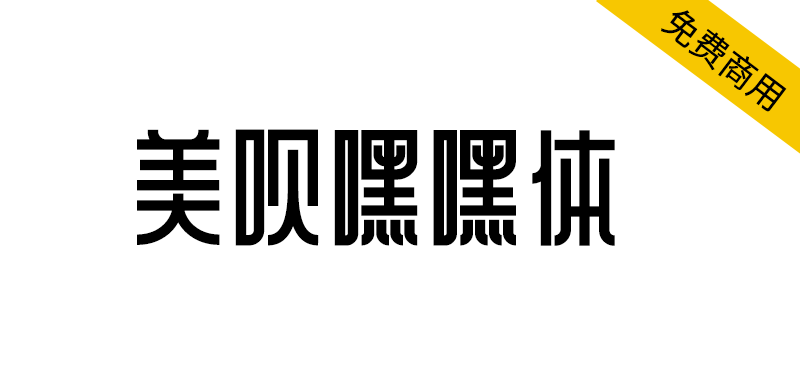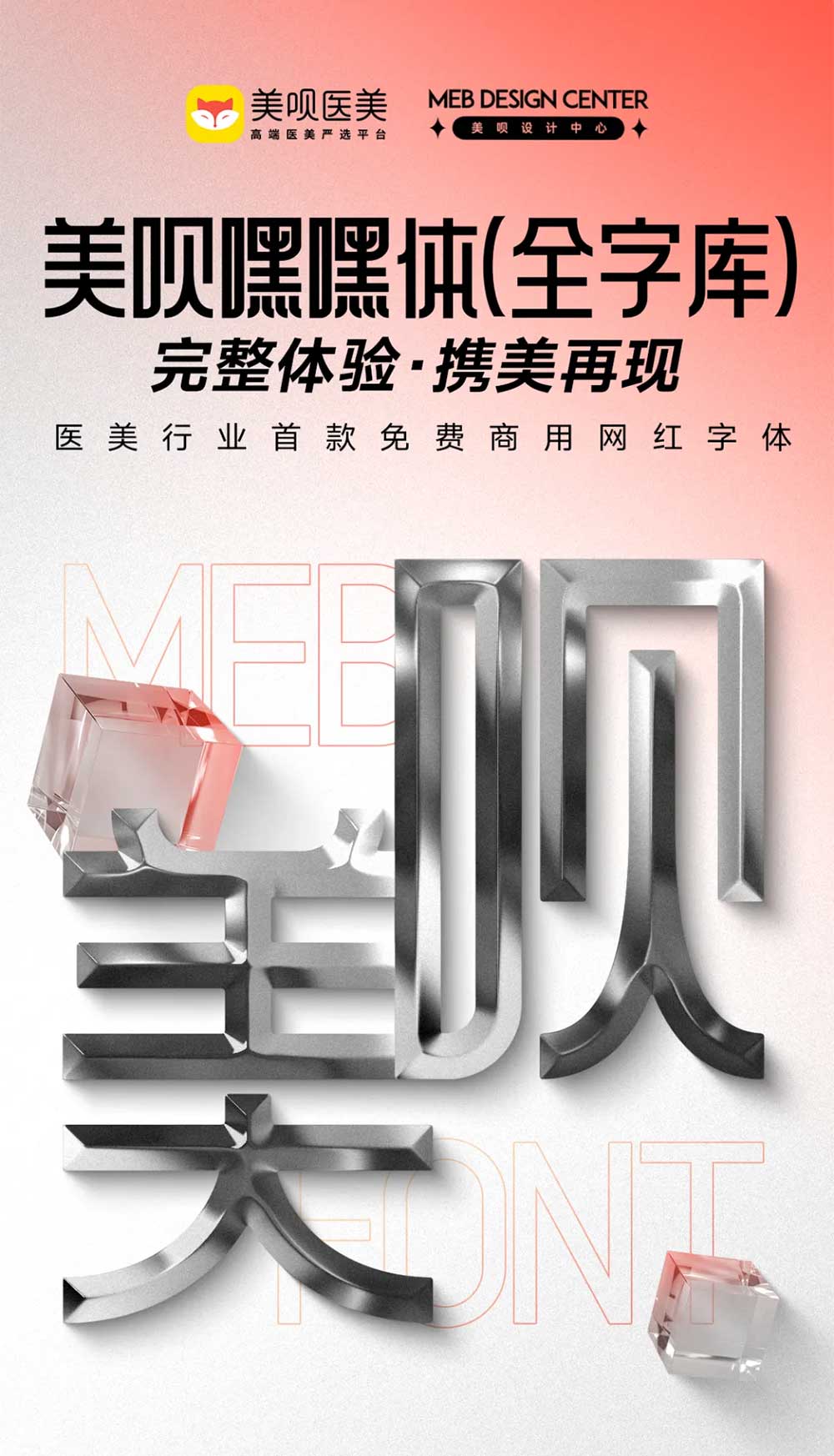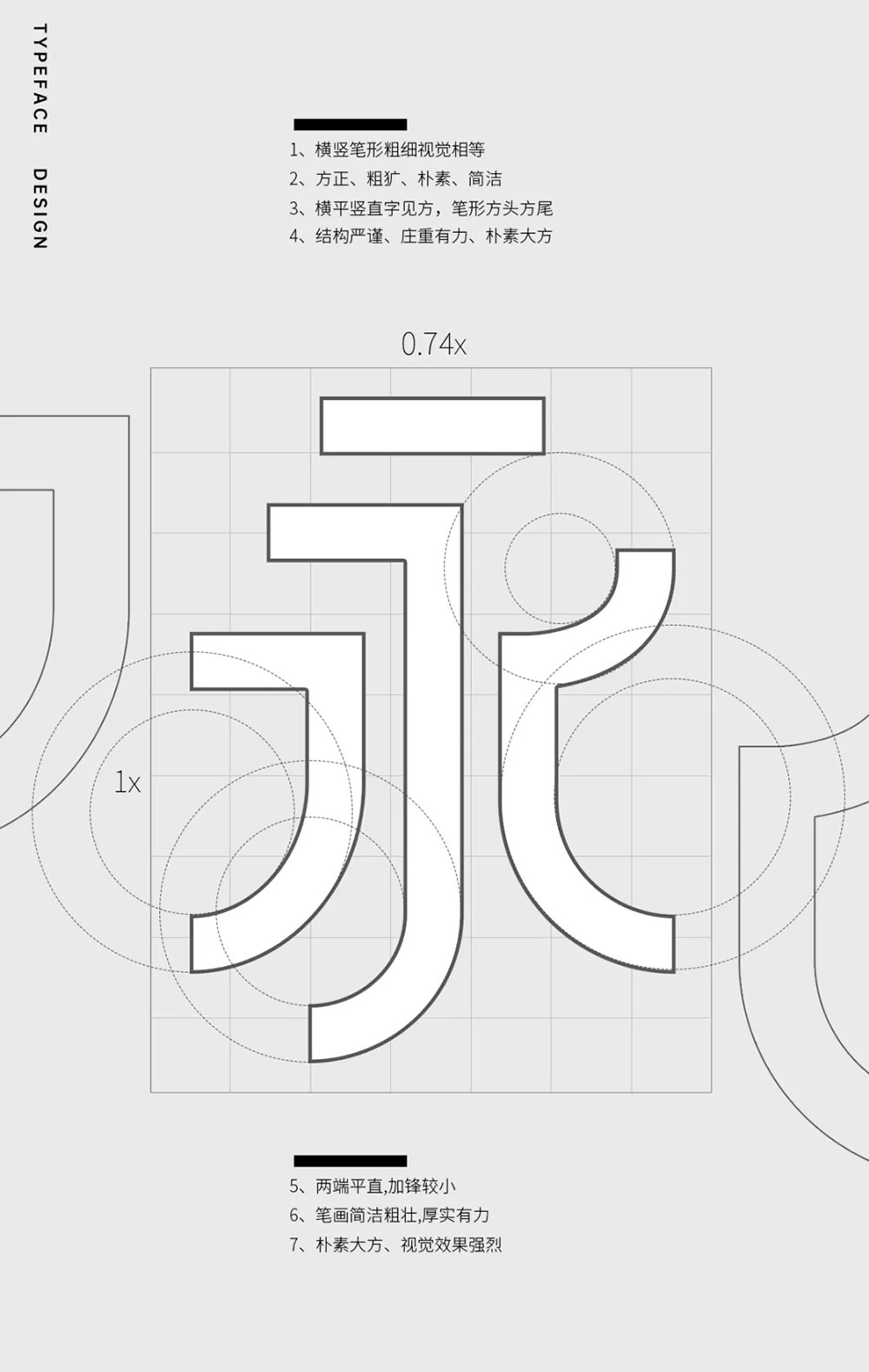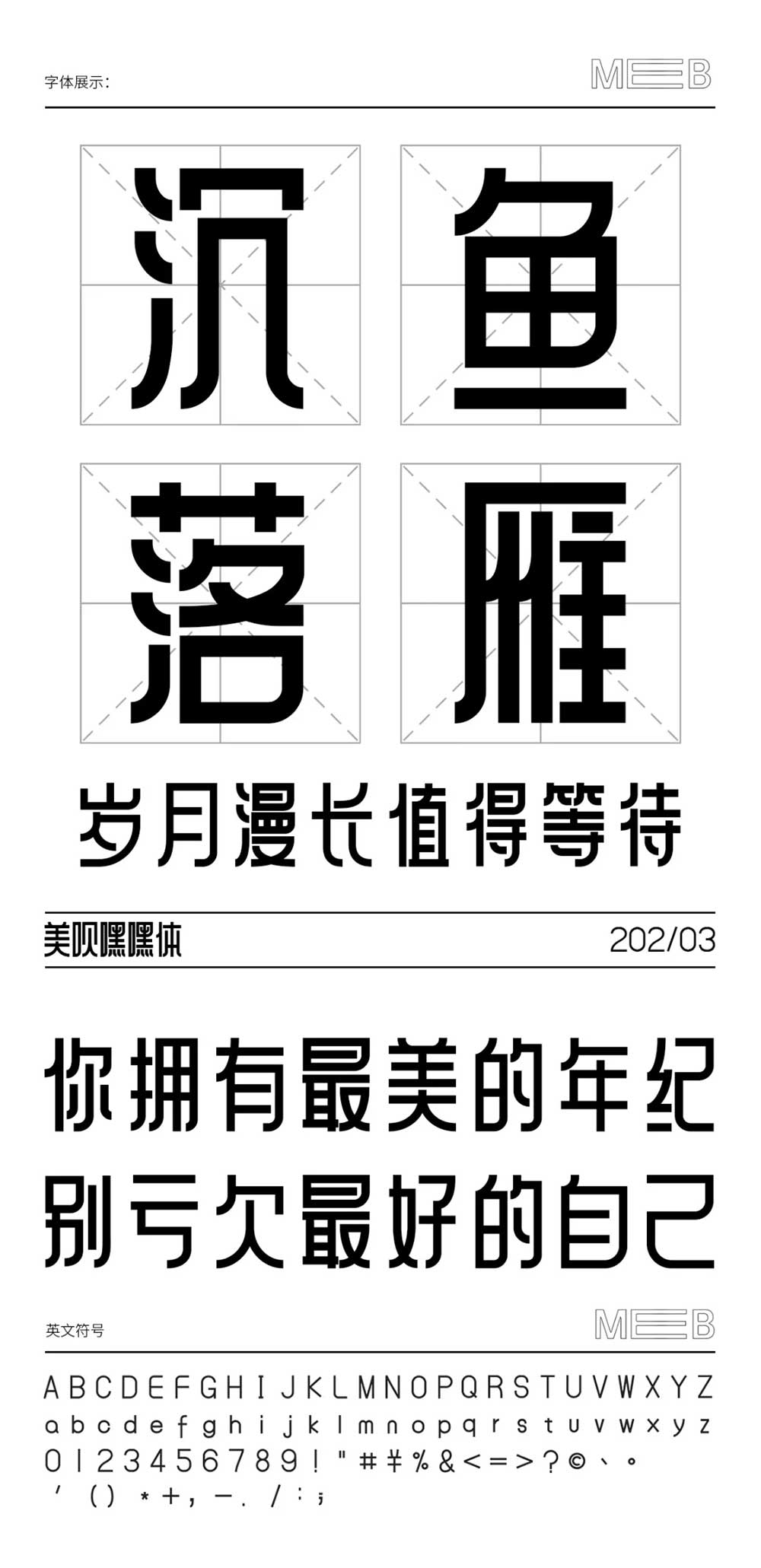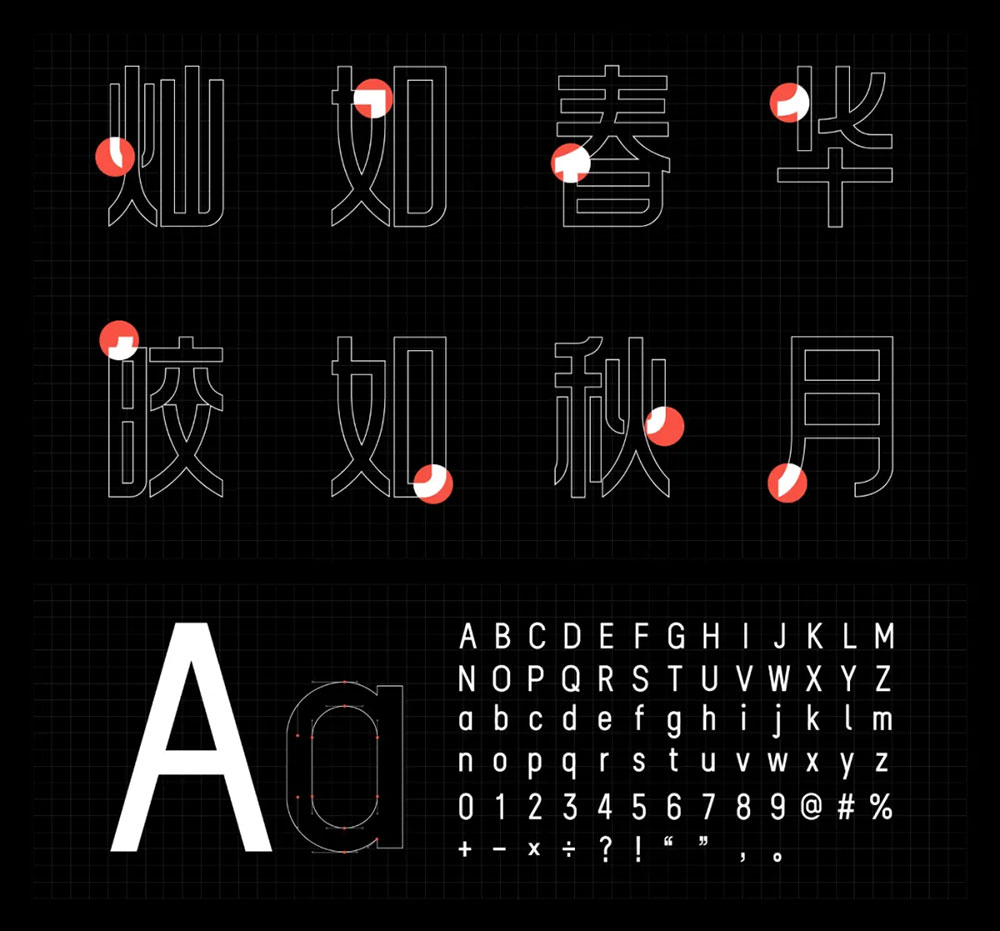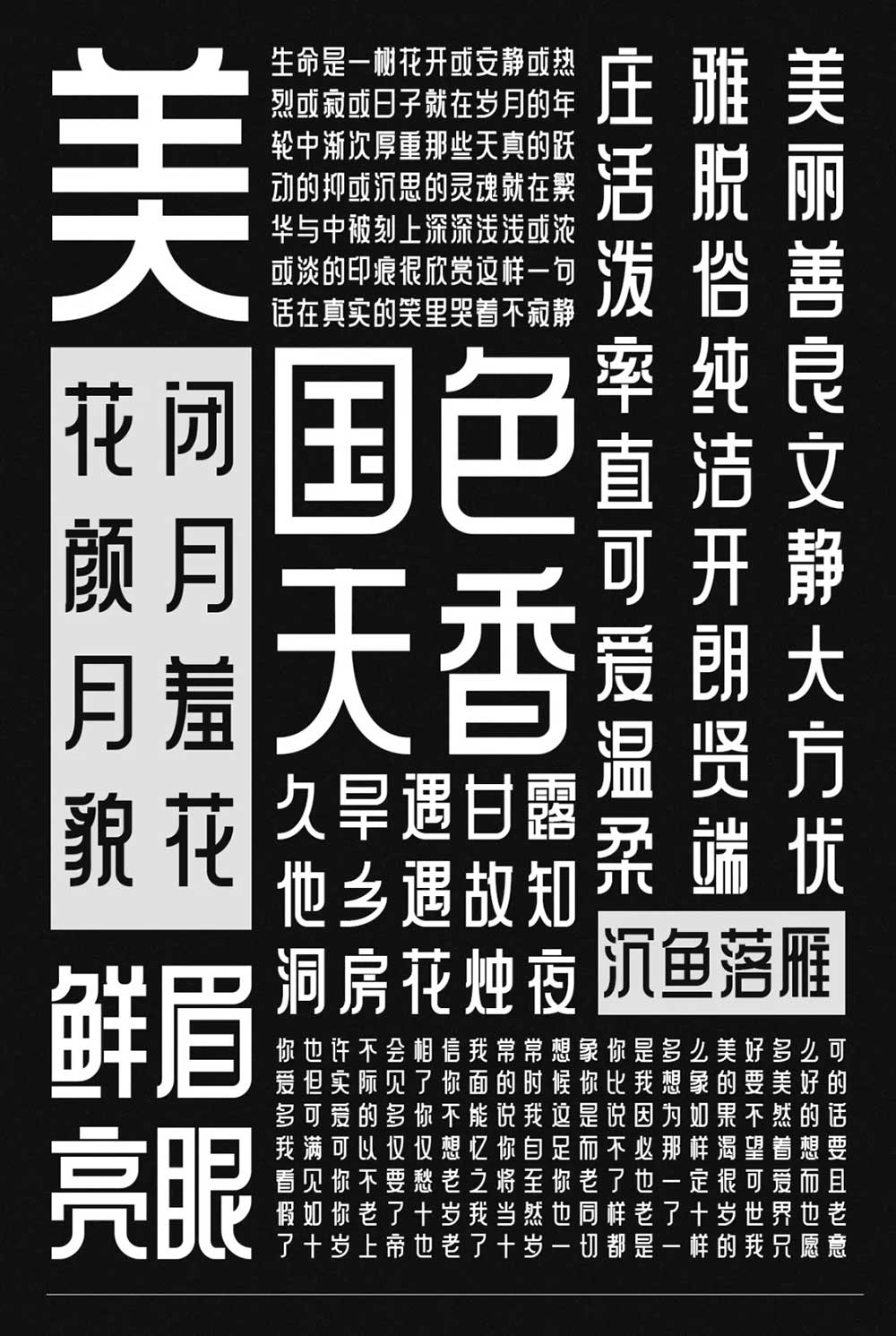
美呗嘿嘿体,是由美呗设计中心主导设计的一款品牌字体,也是医美行业首款字体。之所以取名美呗嘿嘿体,一是因为这款字体本身属于黑体,二是融入了美呗人“乐观、皮实”的精神,故取名“美呗嘿嘿体”。符合GB2312简体中文编码字符标准的品牌字体,包含6767个中文字符和150+西文及数字符号。
秉承公司文化价值观,设计团队在工作之余从构思到完成,整整花了两年半的时间,精心打磨出了一套符合现代美业的商用字体。我们本着“大道至简,大美天成”的设计理念,以极简的笔画形态使字体展现出一种自然美学。在字形设计上,我们采用1:1.4的比例(白银比例),相比西方比较流行的“黄金比例”,在东方更流行“白银比例”,更能体现出低调内敛的东方之美。
美呗一直在为东方女性提供美学服务,我们深知每一位女性都有其独特的美,并且尊重每一种美。我们将11年深耕东方美学的经验,刻入美呗嘿嘿体的设计中,赋予字体大气的东方韵味和温婉的东方美学,让其不仅仅是一个个单调冰冷的字符,更是美呗对于美的理解和诠释。现在免费供大家使用,也是希望能够以己之美,成人之美。